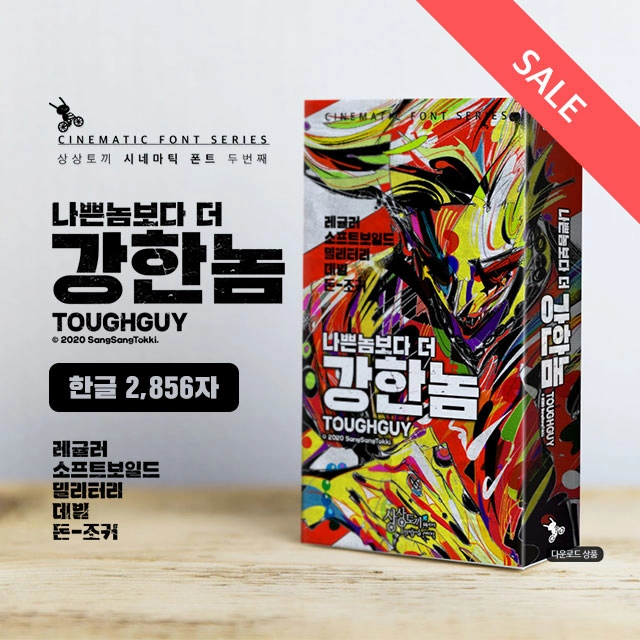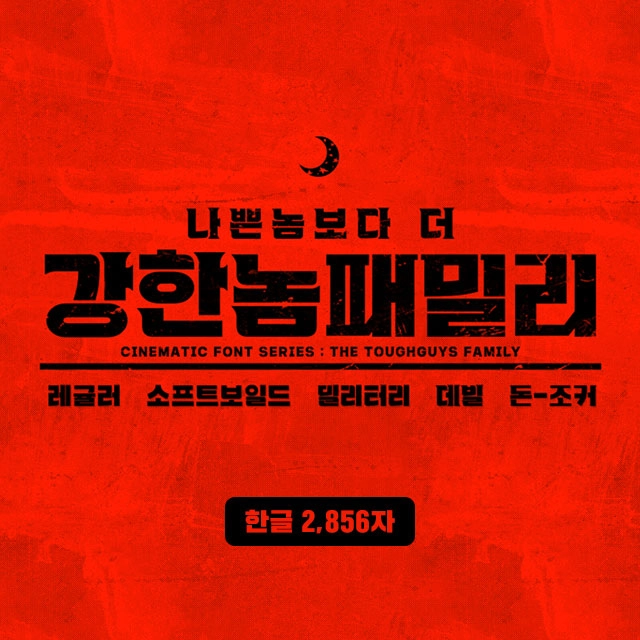
강한놈 패밀리 5종
나쁜놈들보다 더 강한놈들, 강한놈 패밀리 5종 (한글 2,856자)
한글 2,856자 / 영문 52자 / 약물 84자
강한놈 Regular 1종
강한놈 Softboiled 1종
강한놈 Military 1종
강한놈 Devil 1종
강한놈 Don-Joker 1종